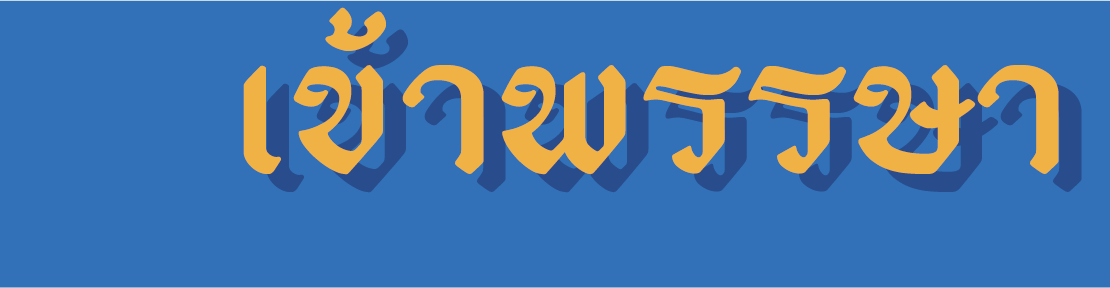
ได้แรงบันดาลใจมาจากตัวริบบิ้นที่พบเจอตามป้ายวัดในชุมชนต่างๆ พยายามออกแบบให้ความรู้สึกเก่าๆ บ้านๆ วัดๆ ห่างๆไกลๆ รวมถึงพยายามลบมุมต่างๆให้มล ไหลๆ เป็นที่มาของชื่อ น้ำมล
EDNamMool (อีดีน้ำมล)